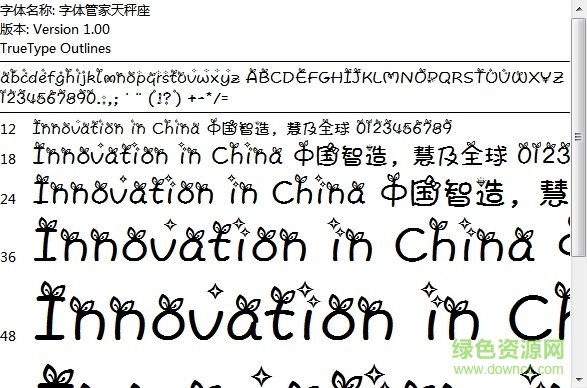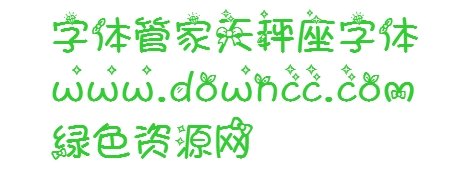
字體管家天秤座
天秤座字體同樣是在胖丫兒字體上進(jìn)行修飾而來(lái),采用了較多的綠葉、蝴蝶結(jié)等可愛(ài)圖案,讓靜態(tài)的文字都擁有布林布林的閃光美感,給你專屬星座字體的美好體驗(yàn),快來(lái)綠色資源網(wǎng)試試吧!
字體管家天秤座字體特色
天秤座的女孩子比較喜歡打扮漂漂亮亮,亮閃閃的,所以用蝴蝶結(jié)、口紅、小星星來(lái)體現(xiàn)天秤的性格比較顏值控。
綠色資源網(wǎng)小編點(diǎn)評(píng)
aa天秤座字體是aa字庫(kù)推出的十二系列字體之一,中文和英文造型均是采用同一款模板,在文字的修飾上各具特色,讓每個(gè)星座的朋友都能擁有一款專屬字體,更加突顯個(gè)性。